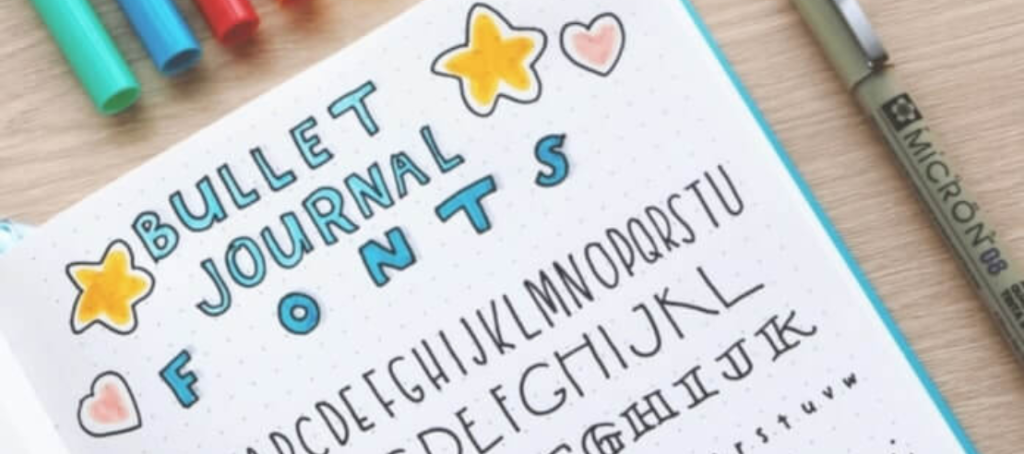
Font Chữ Bullet Journal
Font chữ Bullet Journal là những kiểu chữ thường mang phong cách thủ công, đơn giản và dễ đọc, thường được sử dụng trong việc thiết kế và trang trí các trang Bullet Journal. Những font chữ này thường có nét thanh mảnh, sạch sẽ hoặc mang đậm phong cách viết tay, giúp tạo cảm giác cá nhân và sáng tạo cho từng trang sổ. Sử dụng font chữ Bullet Journal không chỉ giúp làm nổi bật các tiêu đề, danh mục mà còn góp phần tạo nên sự thẩm mỹ và cảm hứng cho người dùng trong việc theo dõi công việc, ghi chú và sáng tạo trong cuốn sổ tay của mình.